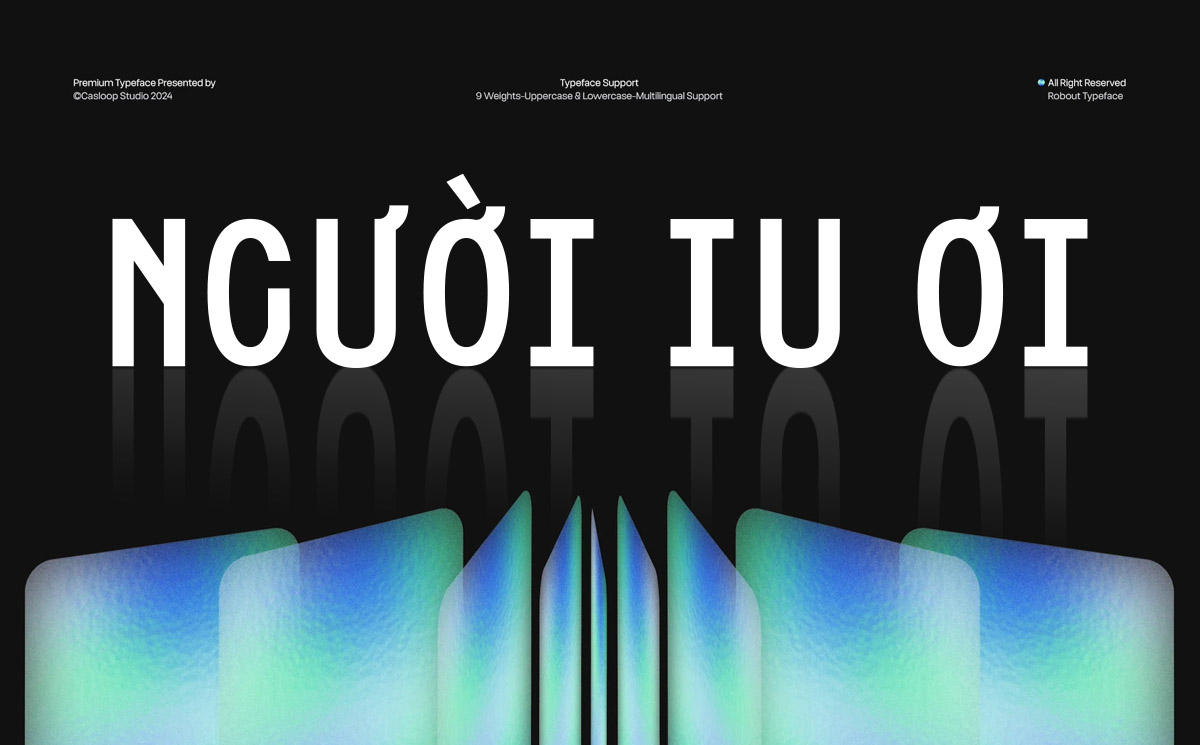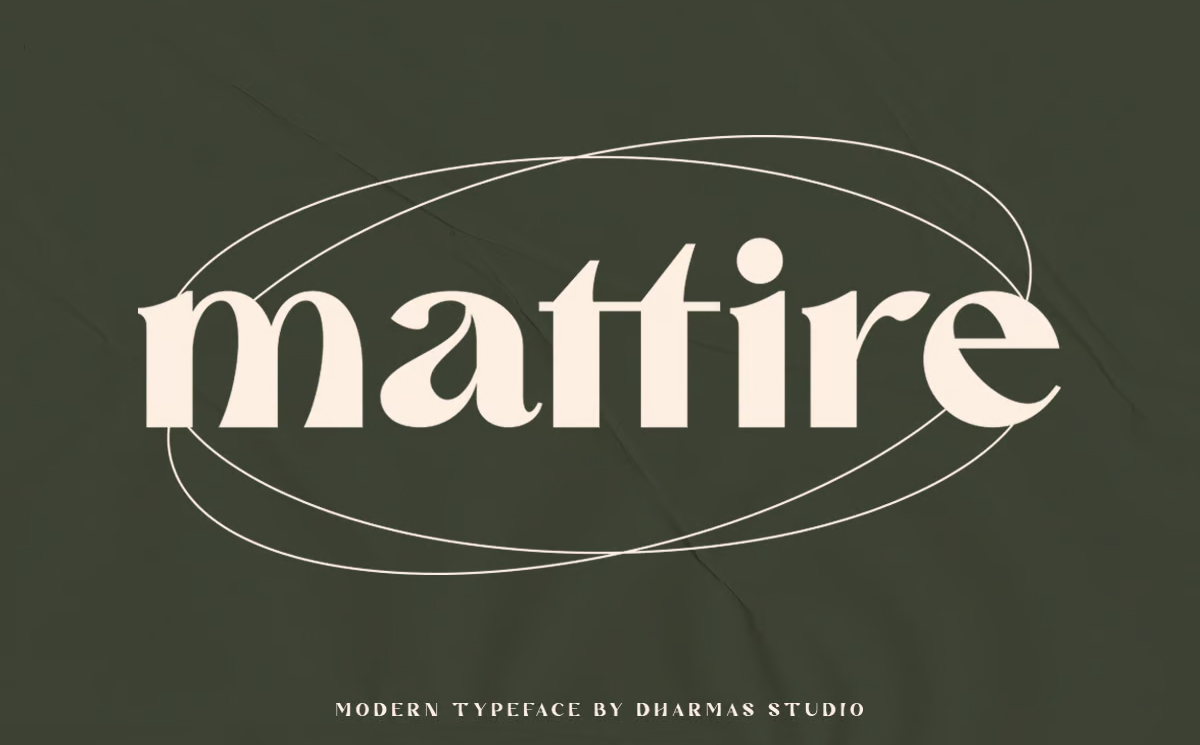
Top 18 font chữ cho bảng giá spa, menu dịch vụ và voucher làm đẹp
Bảng giá spa cần đẹp nhưng trước hết phải giúp khách đọc nhanh tên dịch vụ, thời lượng và mức giá. Menu quá nhiều chữ trang trí sẽ gây rối; ngược lại, thiết kế chỉ dùng một font đơn giản lại dễ thiếu cảm giác thư giãn và cao cấp. Cách hiệu quả nhất là chọn một font có cá tính cho tiêu đề, sau đó phối với font dễ đọc cho phần thông tin.
Bài viết này gợi ý 18 font bảng giá spa Việt hóa phù hợp cho menu dịch vụ, voucher, poster khuyến mãi và các ấn phẩm làm đẹp. Danh sách không lặp lại những font đã giới thiệu trong các bài trước. Mỗi lựa chọn đều có ảnh preview và link đến đúng trang font trên Fontdep để bạn xem kỹ trước khi tải.
Bảng giá spa cần những loại font nào?
Một bảng giá hoặc menu dịch vụ thường cần ba cấp độ chữ:
- Font tiêu đề: dùng cho tên spa, tên bảng giá hoặc thông điệp chính. Font có thể là Serif, Script hoặc Display nhưng cần đủ rõ.
- Font tên nhóm dịch vụ: dùng cho các mục như chăm sóc da, massage, nail, gội đầu dưỡng sinh. Nên có độ đậm vừa và dễ quét mắt.
- Font nội dung và giá: dùng cho tên liệu trình, mô tả, thời lượng và giá tiền. Đây nên là font đơn giản, không quá mảnh và giữ số rõ ràng.
Voucher và poster khuyến mãi có thể dùng font trang trí nhiều hơn vì lượng chữ ít. Với bảng giá dài, hãy ưu tiên Serif hoặc Sans-serif dễ đọc, chỉ dùng Script ở một vài điểm nhấn.
Tiêu chí chọn font cho menu dịch vụ spa
Dấu tiếng Việt phải rõ
Hãy kiểm tra các cụm có nhiều dấu như “Chăm sóc da chuyên sâu”, “Gội đầu dưỡng sinh”, “Thẩm mỹ công nghệ cao” và “Liệu trình trẻ hóa”. Font đẹp nhưng dấu chạm nhau hoặc quá mảnh sẽ làm menu thiếu chuyên nghiệp.
Số và ký hiệu giá cần dễ nhận biết
Bảng giá có nhiều con số, dấu chấm, dấu phẩy và ký hiệu tiền tệ. Luôn thử các mẫu như “350.000đ”, “60 phút” hoặc “Ưu đãi 20%”. Không nên dùng font Script cho toàn bộ phần giá.
Phù hợp với định vị spa
Spa cao cấp thường hợp Serif thanh lịch; spa thiên nhiên có thể dùng chữ mềm và thoáng; thẩm mỹ viện công nghệ nên chọn Sans-serif hiện đại. Font cần đồng nhất với logo, màu sắc, nội thất và hình ảnh đang dùng.
Đọc tốt khi in và trên điện thoại
Menu có thể được in khổ A4, đặt trên quầy hoặc gửi qua Zalo. Hãy kiểm tra thiết kế ở kích thước thật và trên màn hình điện thoại. Font nét quá mảnh dễ mất chi tiết khi ảnh bị nén.
Top 18 font chữ cho bảng giá spa và voucher làm đẹp
1. TH Megan - Serif hiện đại cho bảng giá cao cấp
TH Megan có phong cách Serif hiện đại và sang trọng, phù hợp tiêu đề bảng giá, tên gói liệu trình hoặc khu vực dịch vụ VIP. Dáng chữ tạo cảm giác cao cấp mà không quá cầu kỳ. Khi dùng cho menu, nên phối với Sans-serif rõ nét ở phần mô tả và giá tiền.
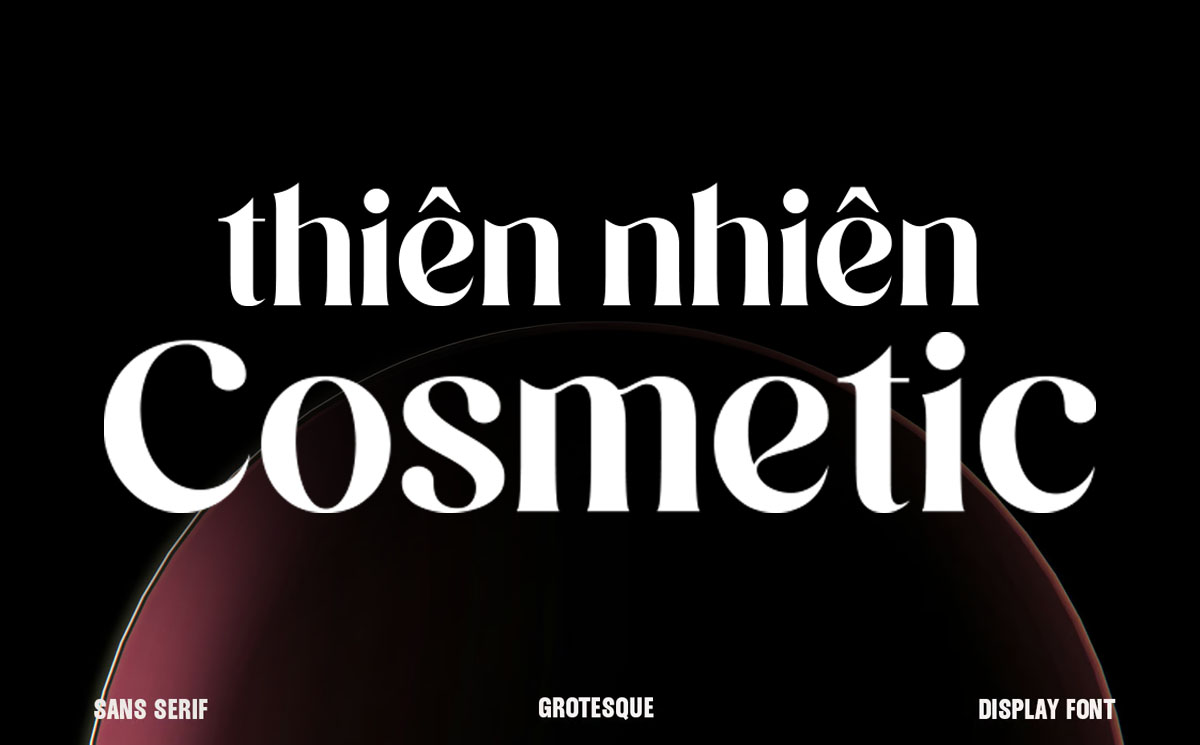
2. TH Erva Esra - Thanh lịch cho tên nhóm dịch vụ
TH Erva Esra kết hợp nét Serif cổ điển và vẻ thanh lịch, thích hợp cho tiêu đề “Chăm sóc da”, “Massage thư giãn” hoặc “Liệu trình chuyên sâu”. Font tạo nhịp điệu nhẹ nhàng, phù hợp menu spa nữ tính và voucher quà tặng.
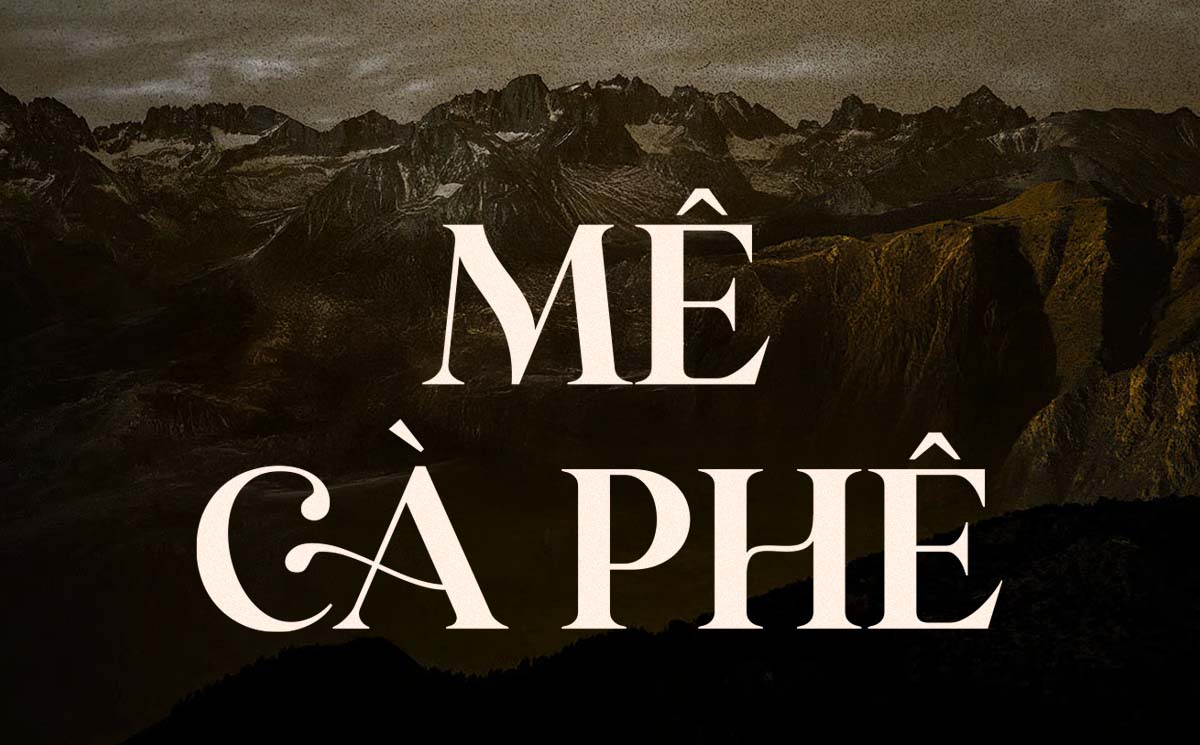
3. TH Ahganirya - Đúng chất thời trang, spa và tạp chí
TH Ahganirya được định hướng cho thời trang, spa và thiết kế tạp chí. Font phù hợp với bảng giá có bố cục nhiều khoảng trắng, ảnh lớn và phần chữ cô đọng. Có thể dùng cho tên spa, tiêu đề menu hoặc headline trên voucher chăm sóc sắc đẹp.
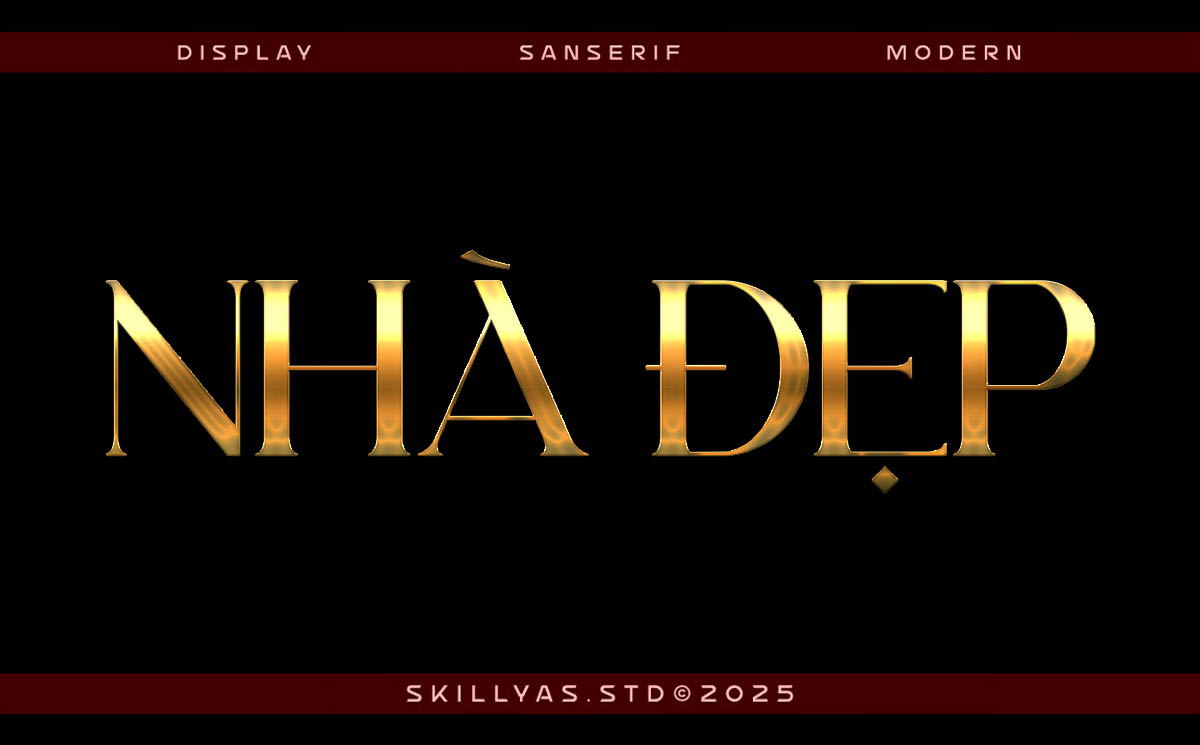
4. TH Kolgar Regular - Nét mảnh cho tiêu đề tinh tế
TH Kolgar Regular có nét Serif hiện đại, mảnh và thoáng. Font đẹp khi đặt lớn ở tiêu đề voucher, tên bộ sưu tập dịch vụ hoặc câu thông điệp ngắn. Không nên dùng ở cỡ quá nhỏ hoặc trên nền ảnh nhiều chi tiết vì nét mảnh có thể giảm độ đọc.
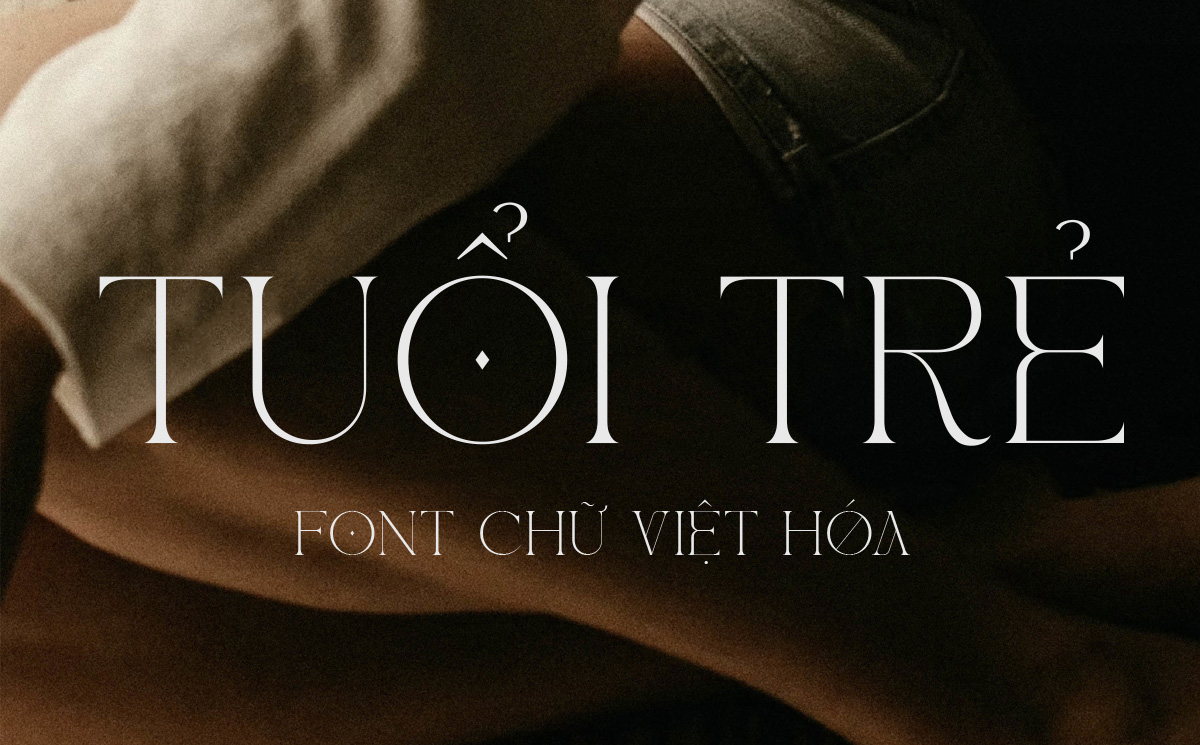
5. TH Milkalte - Sang trọng và hiện đại cho thẩm mỹ viện
TH Milkalte phù hợp thẩm mỹ viện, clinic hoặc spa công nghệ cần hình ảnh chỉn chu và hiện đại. Font có thể dùng cho tiêu đề bảng giá, tên liệu trình nổi bật và các con số khuyến mãi lớn. Hãy phối với font phụ trung tính để phần điều kiện voucher dễ đọc.
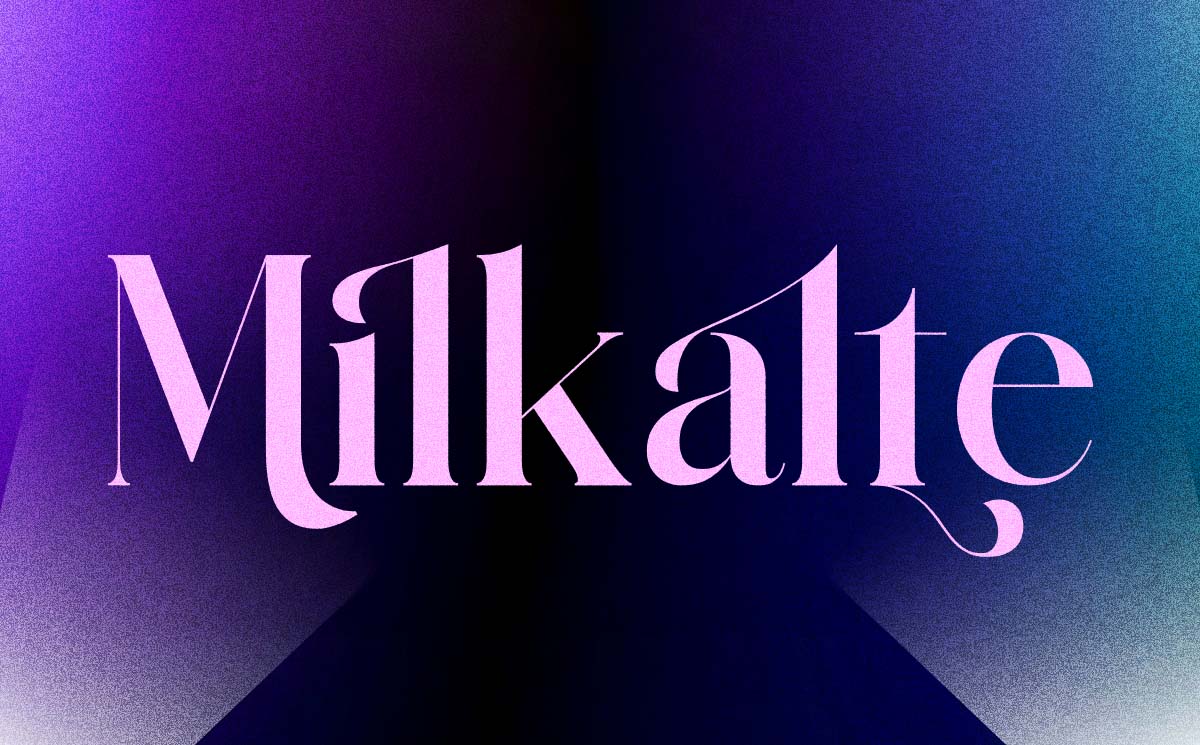
6. TH Barnice - Serif thời trang cho menu làm đẹp
TH Barnice mang tinh thần thời trang, phù hợp salon, spa, nail và thương hiệu làm đẹp hướng đến khách hàng trẻ. Font tạo điểm nhấn tốt ở tên menu và các gói dịch vụ theo mùa. Khi dùng trên bảng giá dài, nên giới hạn ở heading và tên nhóm.
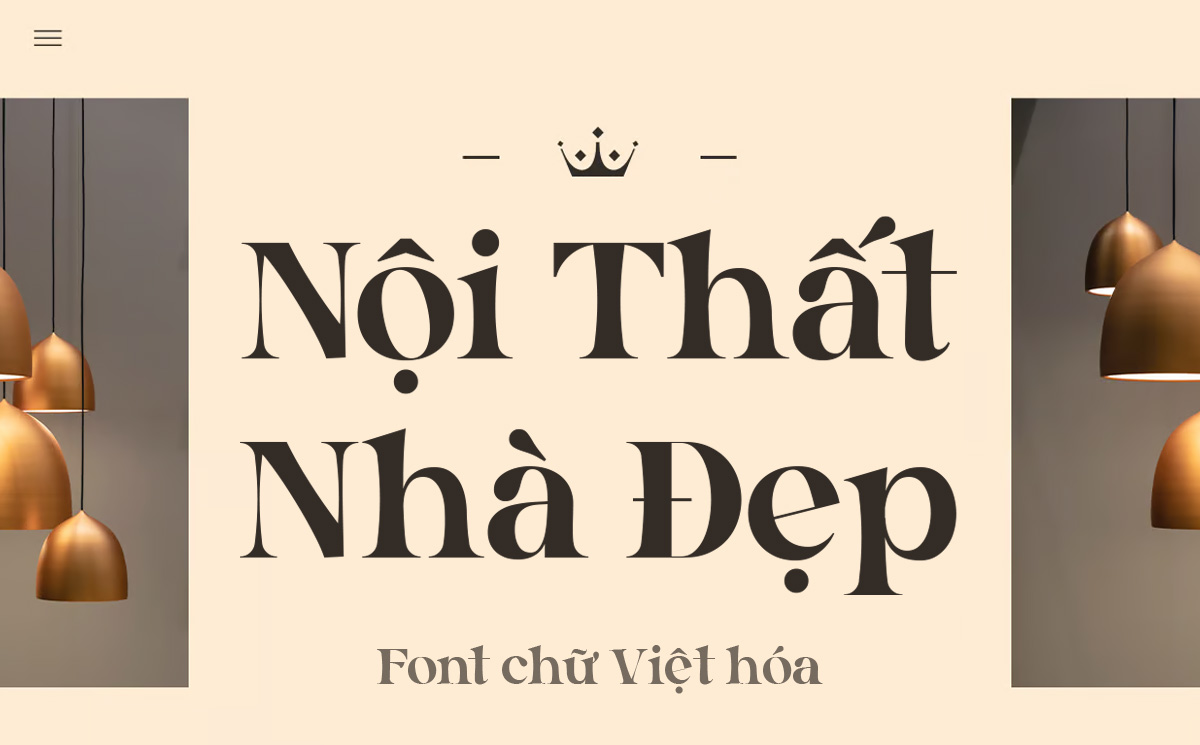
7. TH Grotley - Luxury Sans-serif dễ ứng dụng
TH Grotley là lựa chọn đáng cân nhắc khi bạn muốn cảm giác luxury nhưng vẫn gọn và hiện đại. Sans-serif giúp chữ dễ đọc hơn trong bảng giá, đặc biệt ở tên dịch vụ ngắn và thông tin thời lượng. Font cũng hợp với thẩm mỹ viện dùng bố cục tối giản.
Chọn font đẹp nhưng phải giúp khách đọc nhanh
Font bảng giá spa không chỉ tạo cảm xúc mà còn hỗ trợ khách hàng ra quyết định. Hãy dùng Serif hoặc Sans-serif cho cấu trúc thông tin, Script cho điểm nhấn và luôn kiểm tra dấu tiếng Việt, con số, kích thước thật trước khi chốt.